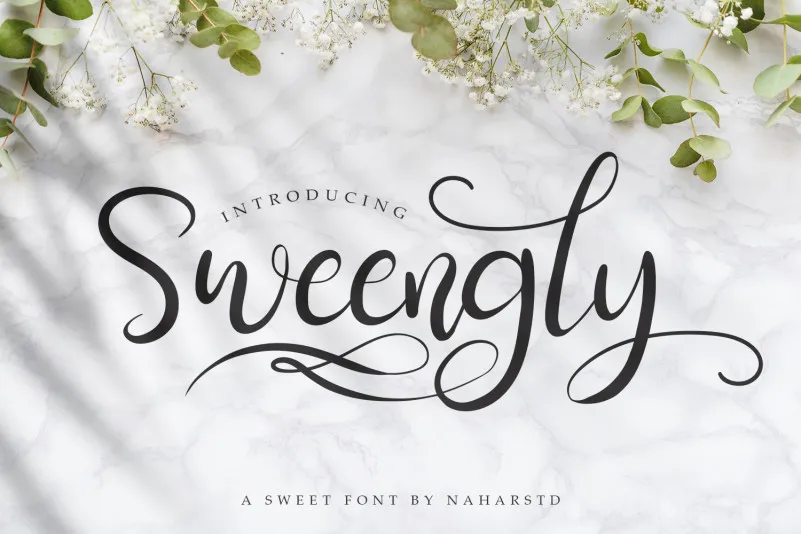
Sweengly – Sweet Script Font – Download Grátis
Sweengly – Sweet Script Font é uma delicada tipografia script que se destaca não apenas por seu charme único, mas também pela sua versatilidade impressionante. Com um gosto de alegria e sutileza que enriquece qualquer projeto visual, esta fonte será ideal para adicionar um toque especial em várias áreas de aplicação. Ideal tanto para projetos como logomarcas, trabalhos de marcação, design de móveis de casa, embalagens de produtos, taças de café, cartazes, sacolas de shopping e até mesmo para personalizar itens de roupas, Sweengly é perfeito para qualquer ocasião especial ou criação que busque um brilho a mais. Suave e encantadora, esta fonte será o ponto final perfeito em qualquer projeto design. Seja na ilustração de livros, cartões de convite, cartas de cumprimentos, etiquetas, fotografia ou até mesmo como marca d’água para eventos especiais, Sweengly – Sweet Script Font está aqui para tornar seu trabalho ainda mais especial e encantador.